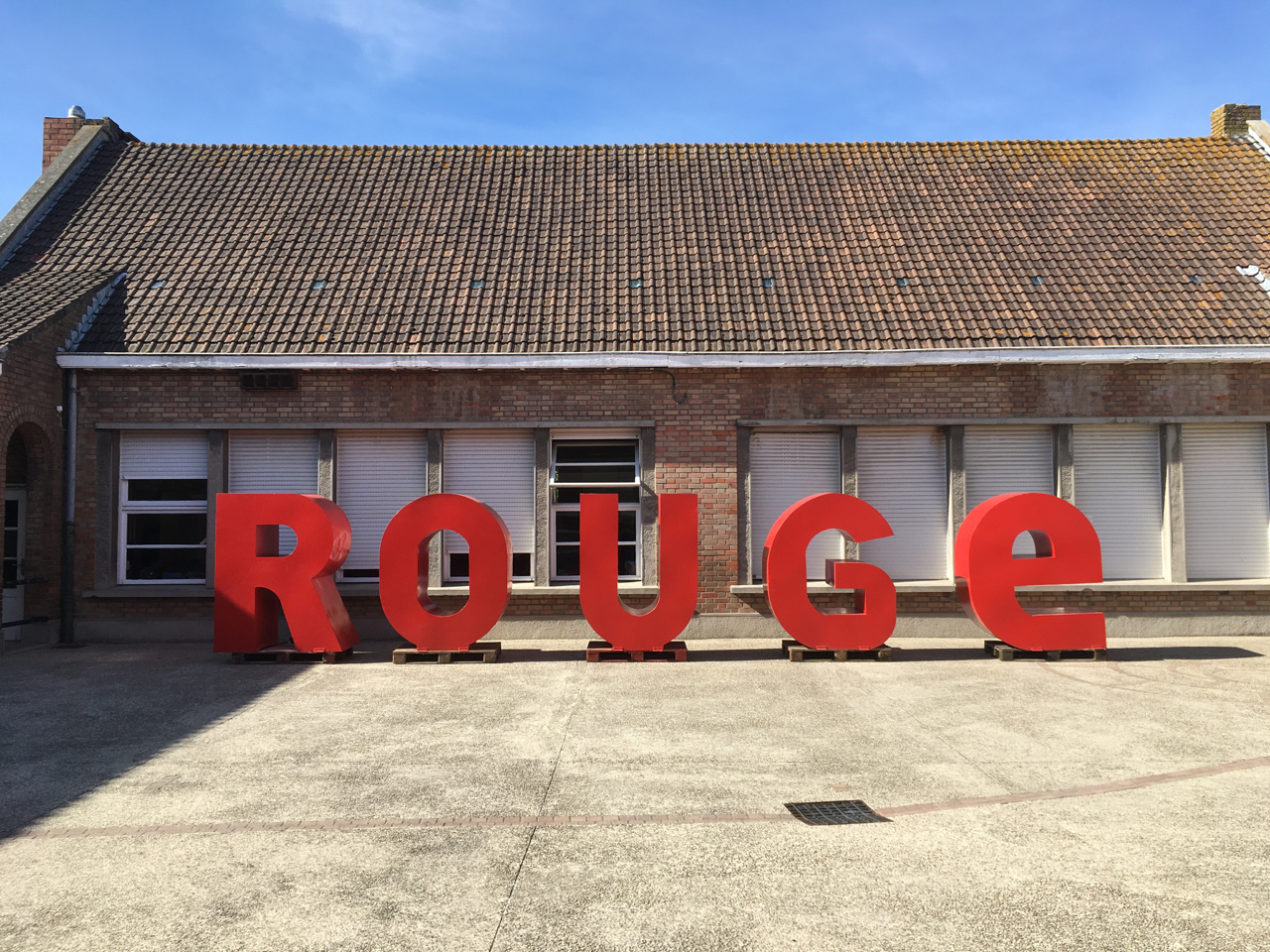
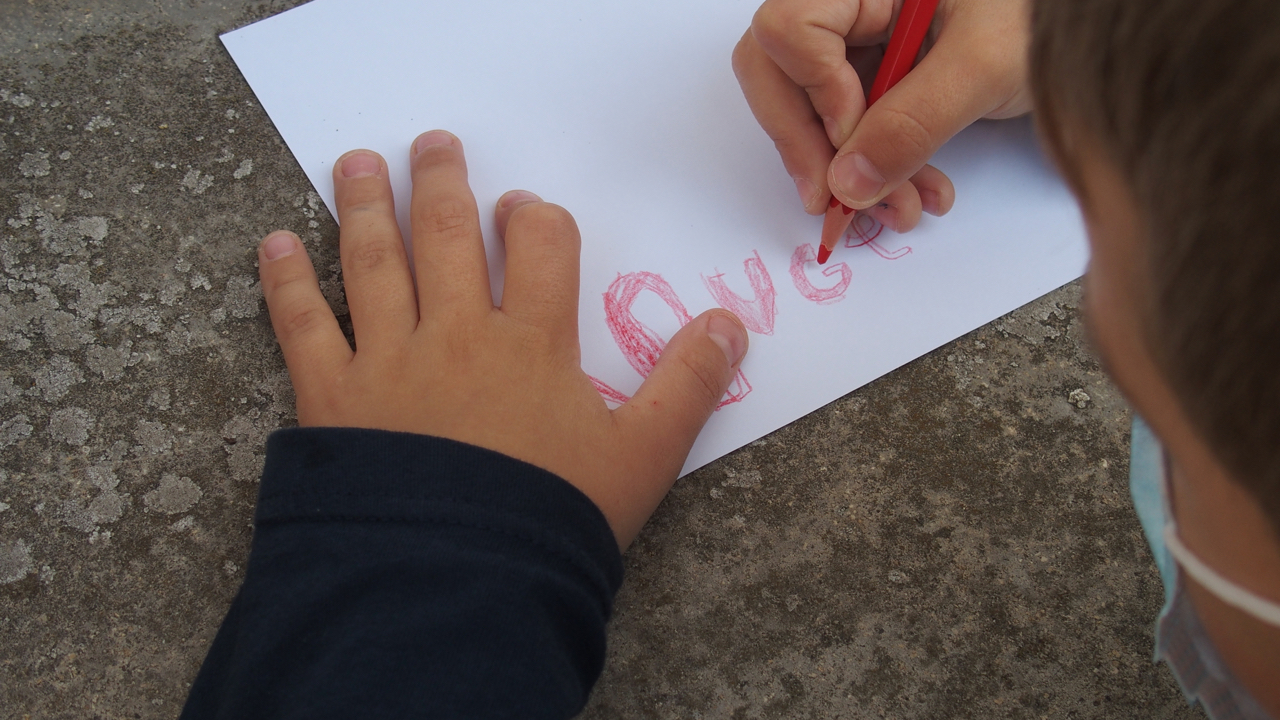
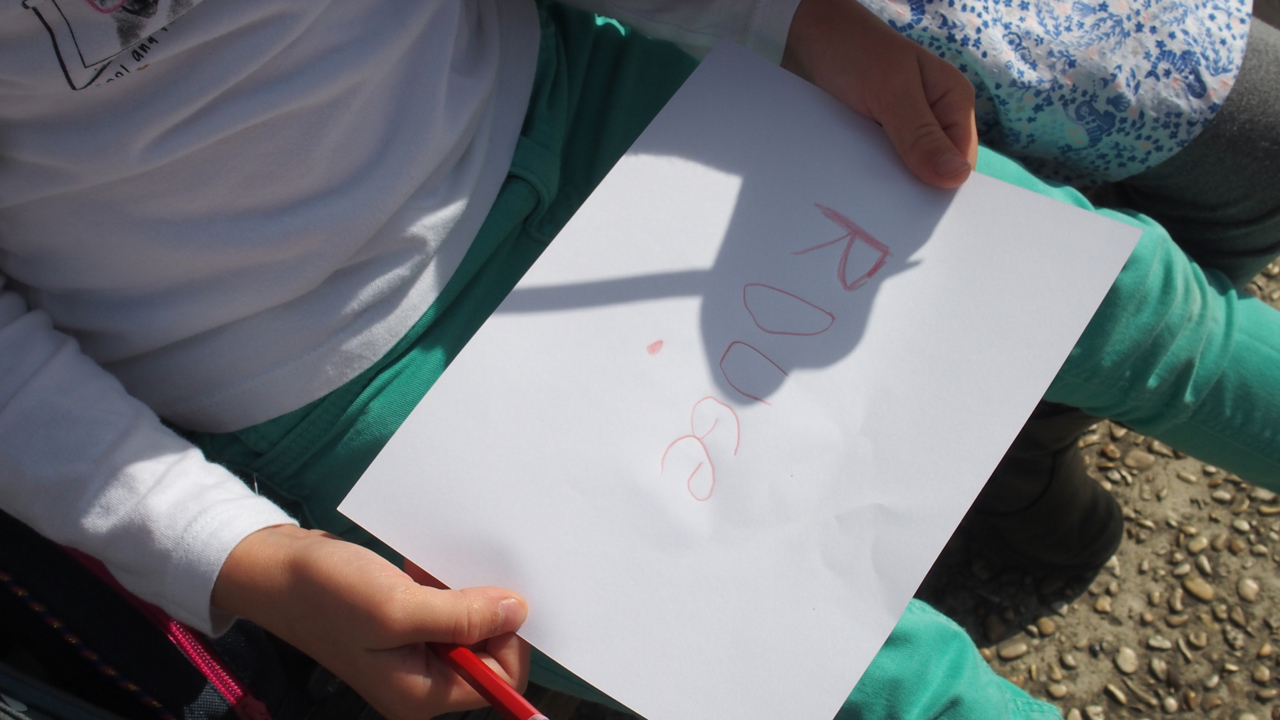
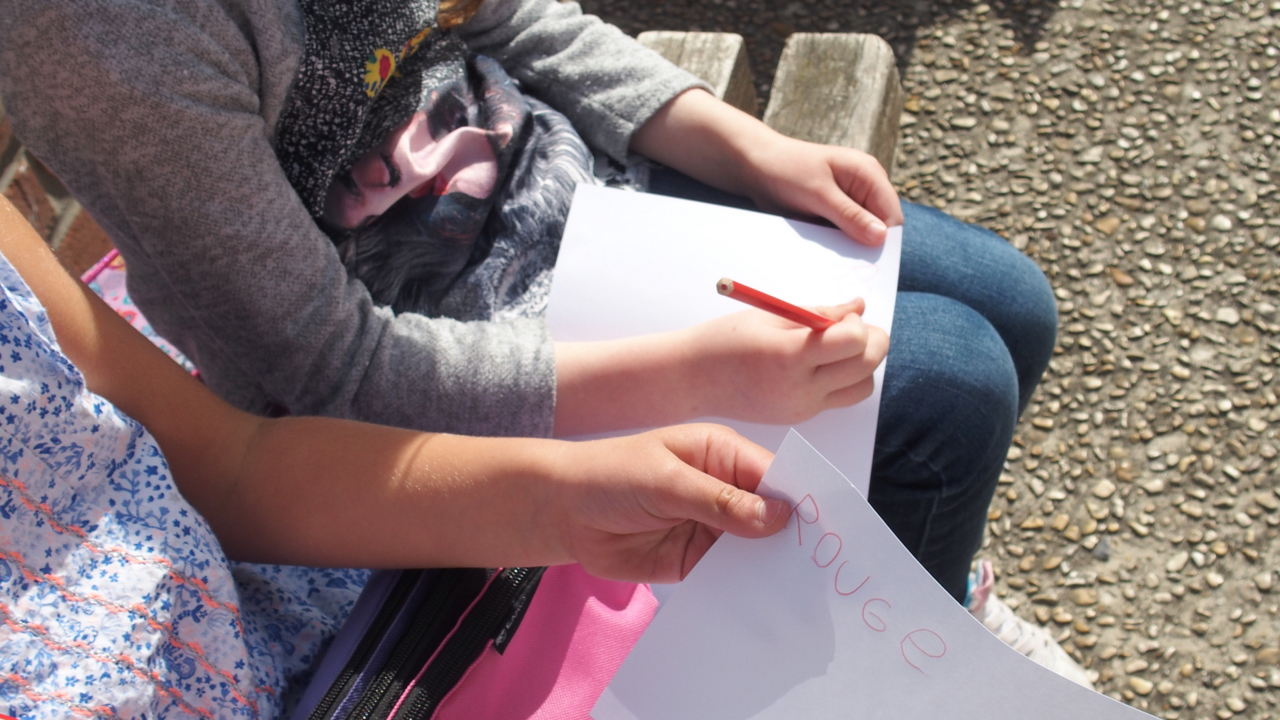
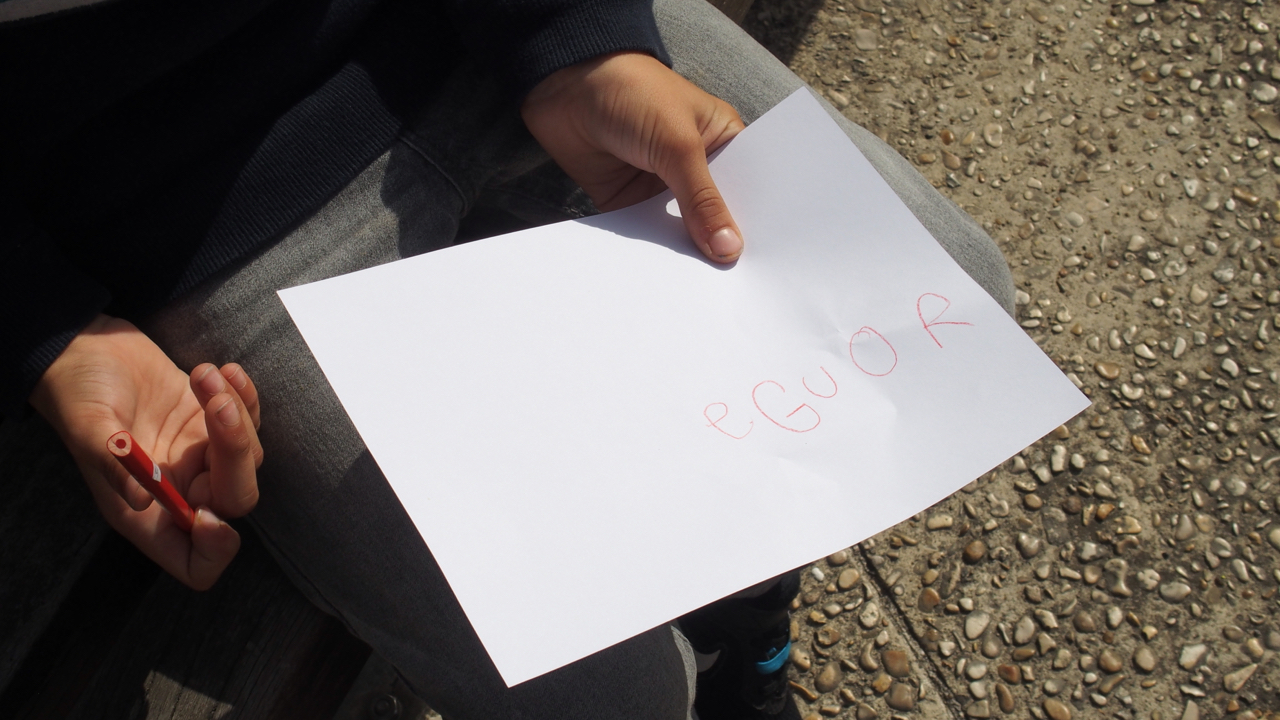
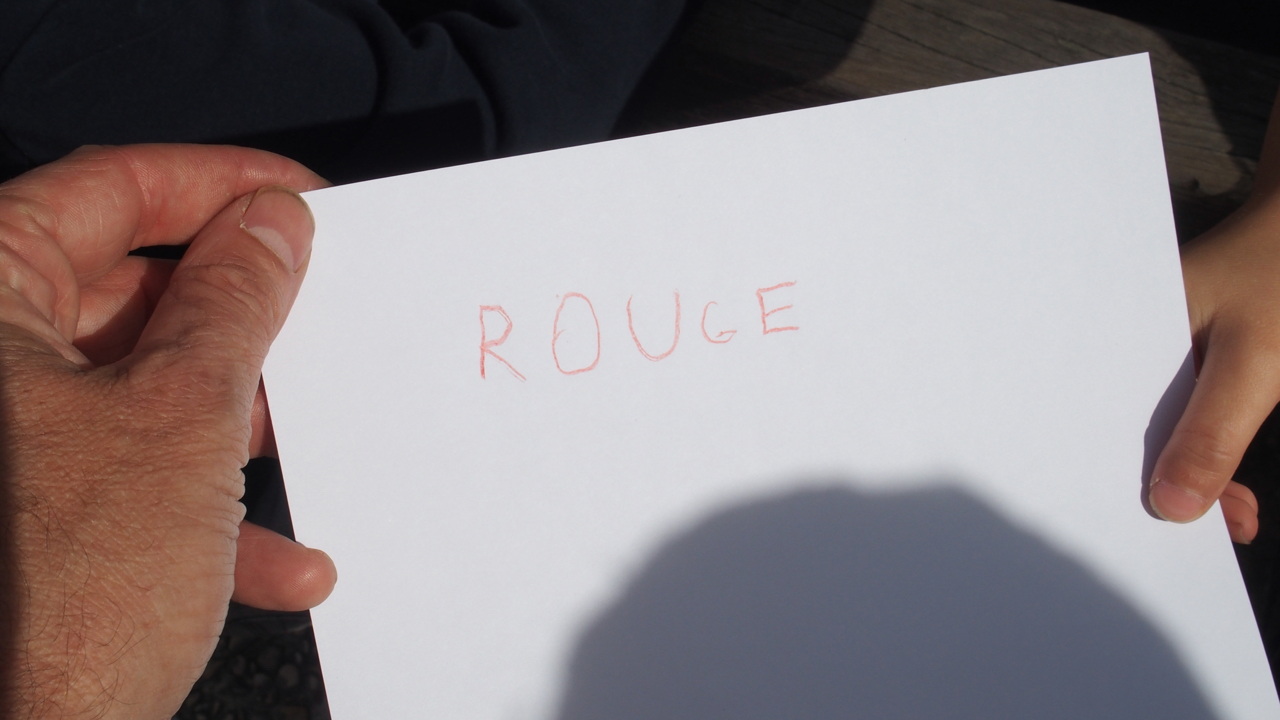
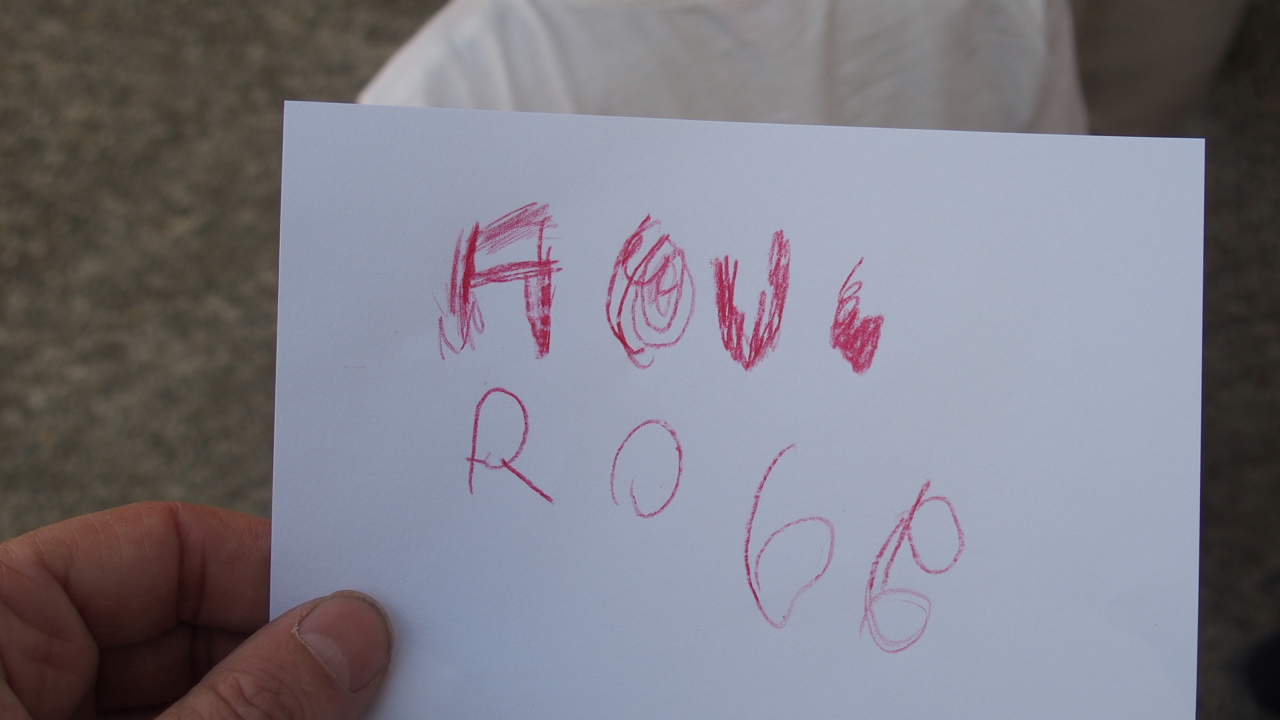
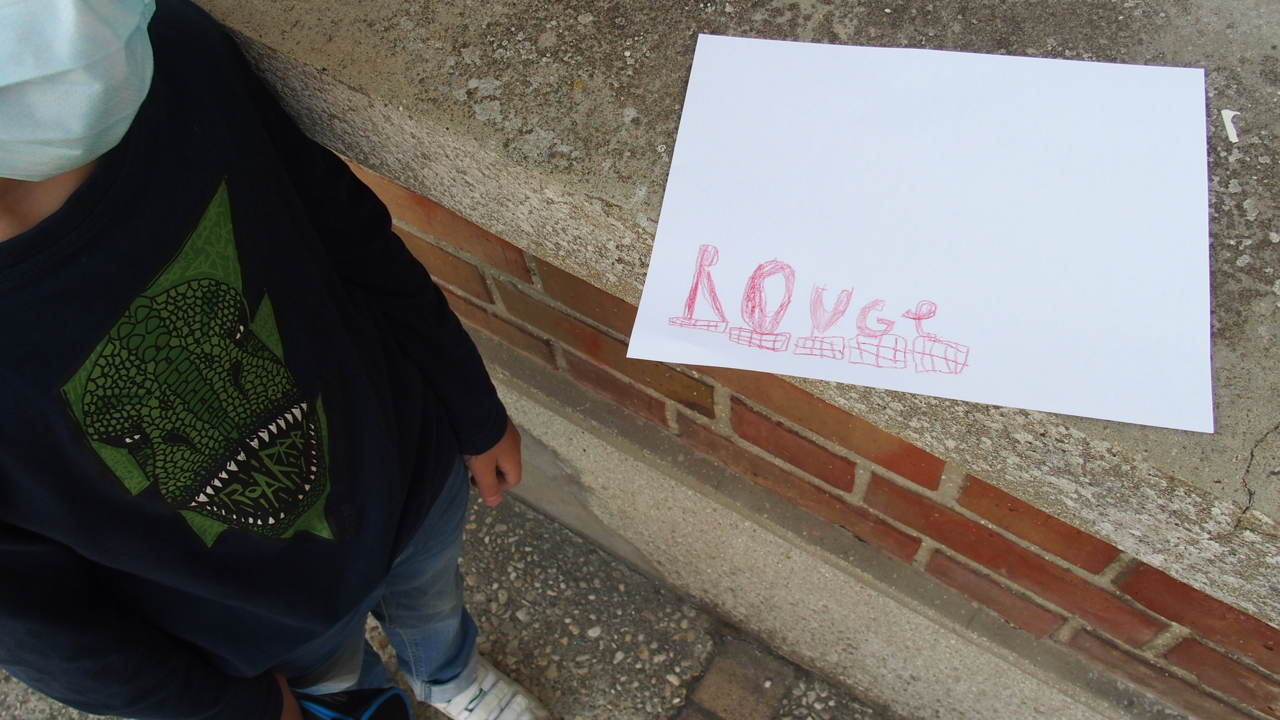
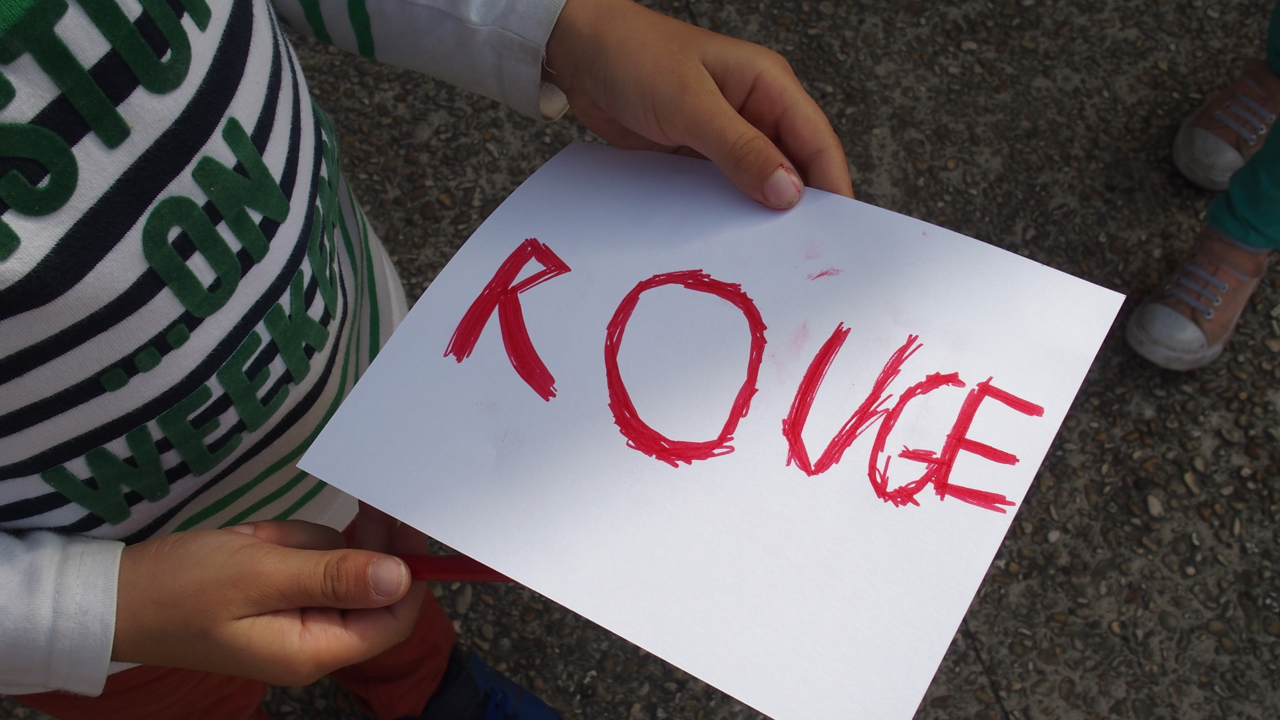
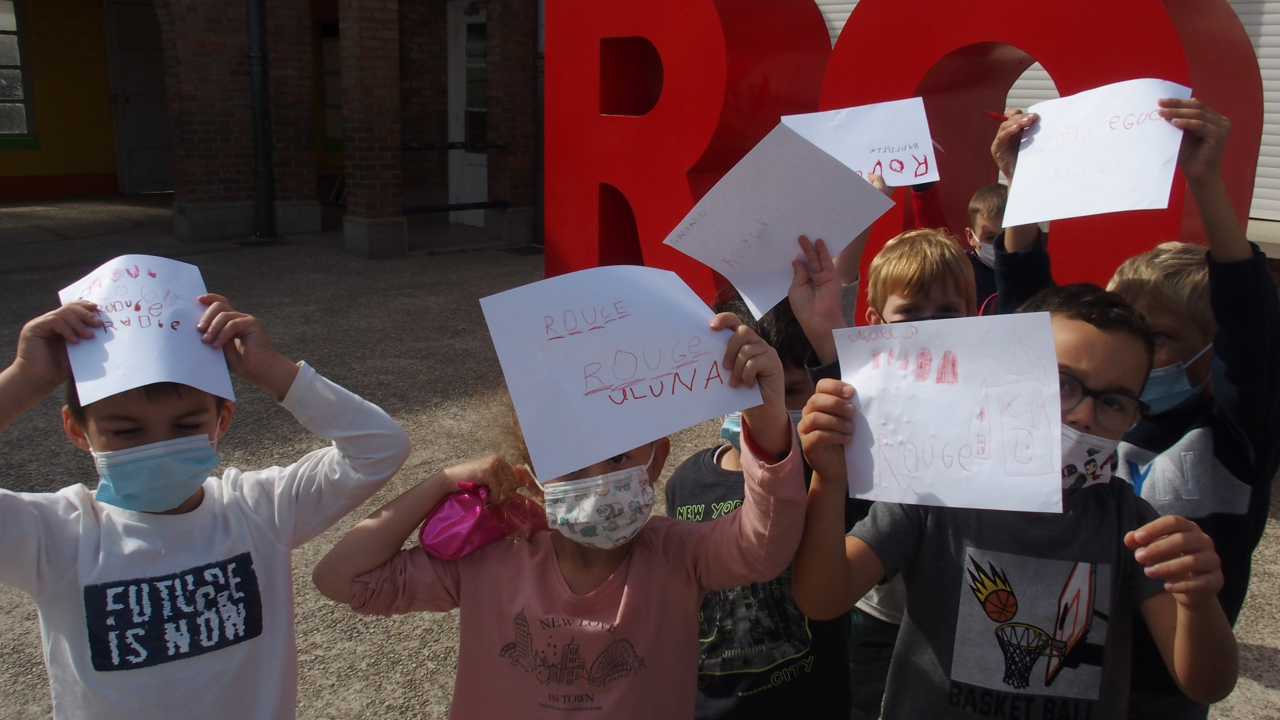
On parle. Lettres, langage et formes. Typographie. Et on sort voir le gros ROUGE, pour le dessiner.
Comme un paradoxe. Dessiner un mot. D’après nature.
Percevoir et rendre.
Noter la perte entre les deux. Comme ces fois, où le E final n’est pas dessiné mais réécrit. D’autres mettent du volume dans les lettres. D’autres les palettes. Et tous forment une palette de rouges, de teintes différentes, d’un monochrome de départ.
Et voilà que les dessins sont signées: nait alors le Rouge Luna, le Rouge Céleste, le Martin Rouge, le Rouge Rouge Chloé…
On sort les petites lettres des Letterboxes, pour écrire des couleurs. En rouge. I vert. L’automne est là. Pas le temps de parler de Rimbaud.
Puis des prénoms, comme une récompense identitaire, s’inscrire là en lettres rouges. Tout le monde y passe, je ne garde que Chloé pour ce regard jeté voir si l’accent est bien placé. Et puis le JULES -j’ai pris la photo 3 fois- parce que dans la classe y’en avait trois, trois JULES.
À eux, propres, de faire la différence. De carner leur prénom, identique, à leur façon.
Ils ont tous des t-shirts avec des inscriptions en anglais, on les passe en revue, dont un « BKLYN », je lui explique Brooklyn, New-York, le pont. L’anglais Brook, rivière. Un me dit « Comme Brouckerque! ». Et d’expliquer l’église qui se cache dans le –kerque. L’église des marais. De parler d’Hazebrouck, le marais aux lièvres, de Dunkerque, l’église de la dune.
D’expliquer le flamand, le néerlandais… »broek », l’allemand « bruch », les variantes: Brouck, Broucq, Broucque.
Brooklyn vient des néerlandais qui en 1624 achètent aux Mohawks le territoire sur lequel ils fondent le village de Breuckelen — la première municipalité de la Nouvelle-Néerlande, du nom de la ville de Breukelen aux Pays-Bas et qui deviendra Brooklyn par la suite.
Et puis ces petits moments de chaos vers, à chercher comment écrire, bricoler un A, pour un instant très chorégraphique souvent dans les expressions de chacun, les rôles, les échanges, une composition naturelle, une petite communauté s’organisant pour former le drapeau de l’instant. Là le prénom de Sacha.
De la chorégraphie sauvage, car non écrite.
Juste un prétexte, sous tendant le tout, un prénom, soudainement formant communauté active.
À écrire.
Ensemble.
Tous tournés vers ce « A ».
Ne peux m’empêcher de penser au très beau roman de Nathaniel Hawthorne, La lettre écarlate.
Un des premiers romans de la littérature américaine, autour d’une communauté protestante, puritaine sur la côte est, à quelques encablures de Brooklyn. Tout se boucle.